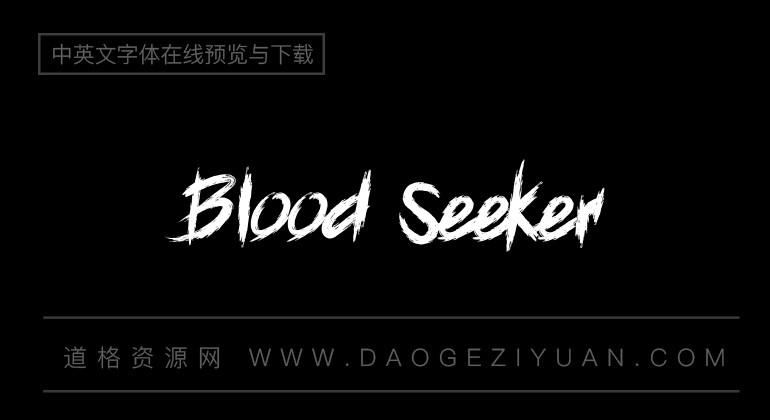
Blood Seeker 字体是一种被设计为略带恐怖和血腥感觉的字体。它采用了类似于刀刻字体的设计,字母笔画粗细不一,边缘显得有些粗糙,同时每个字母还伴随着一些血液的纹理,使得整个字体看上去更加逼真。在视觉上,Blood Seeker 字体有一种令人不寒而栗的感觉,非常适合用于恐怖、血腥、犯罪等主题的文本和设计作品。内容介绍
Blood Seeker是一款非常不错的手写艺术字体,具有很好的视觉感,适合于文化类的宣传设计、商业类品牌的广告和产品包装设计以及个性化文字排版等较多场景。